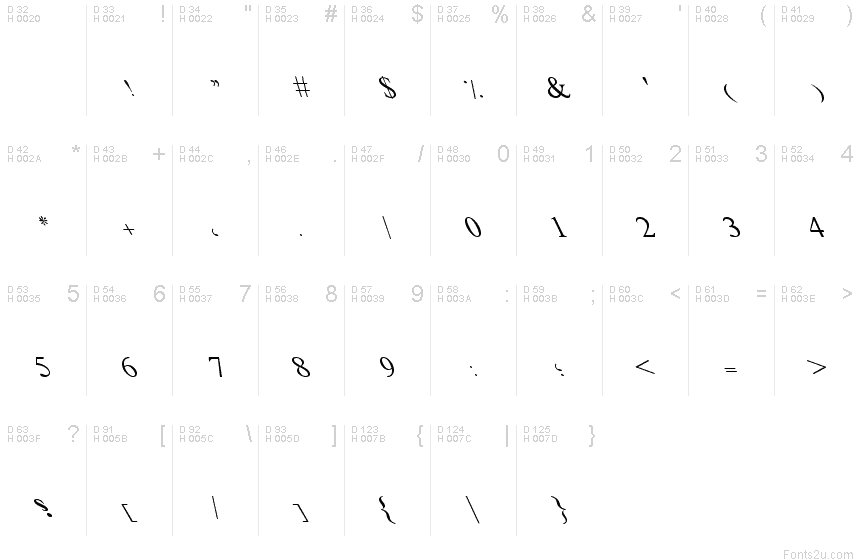
Urdulife Italic di UrduLife è un font calligrafico arabo gratuito dal ritmo fluido e calligrafico. Le lettere si intrecciano con curve ampie e tratti affusolati, donando al carattere un aspetto vivace e colloquiale, lontano dalla rigidità formale.
Ideale per il branding di progetti culturali, titoli editoriali, copertine di libri, poster di eventi e packaging che richiedono un tocco caldo e artigianale. Essendo un font gratuito, è perfetto anche per titoli brevi, citazioni e bozzetti di loghi, poiché il movimento delle lettere infonde dinamismo e una sensazione di autenticità anche alle parole più brevi.